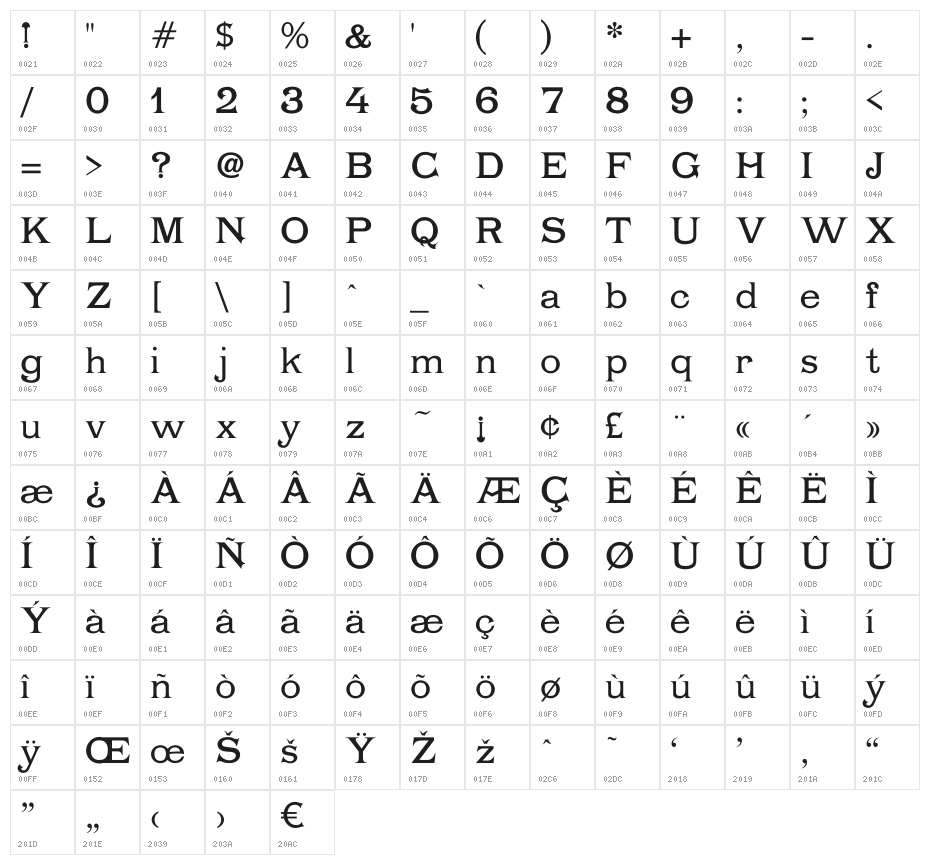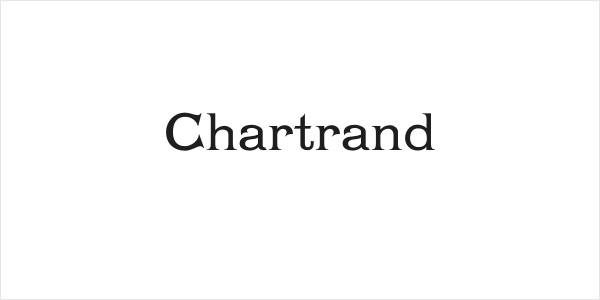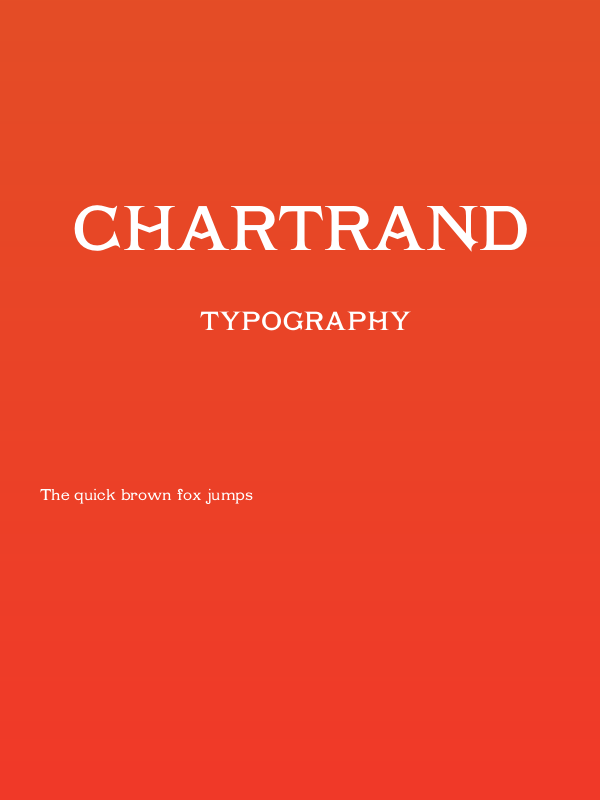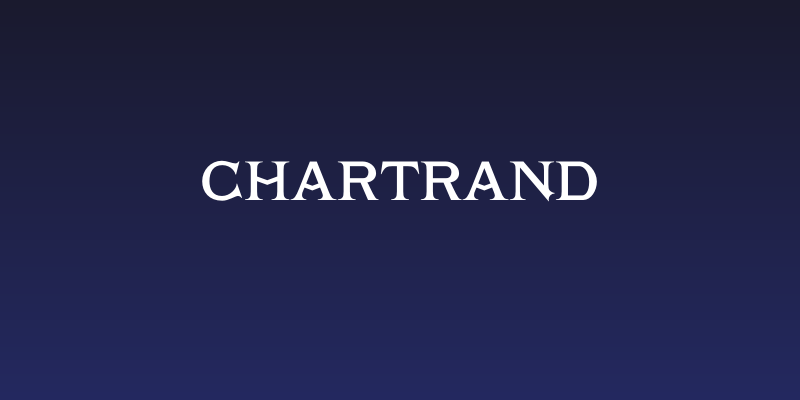
Chartrand Font
✎ Serif
| Progetti proposti | Ideal for editorial design, book covers, formal invitations, and branding projects that require a touch of elegance and tradition. |